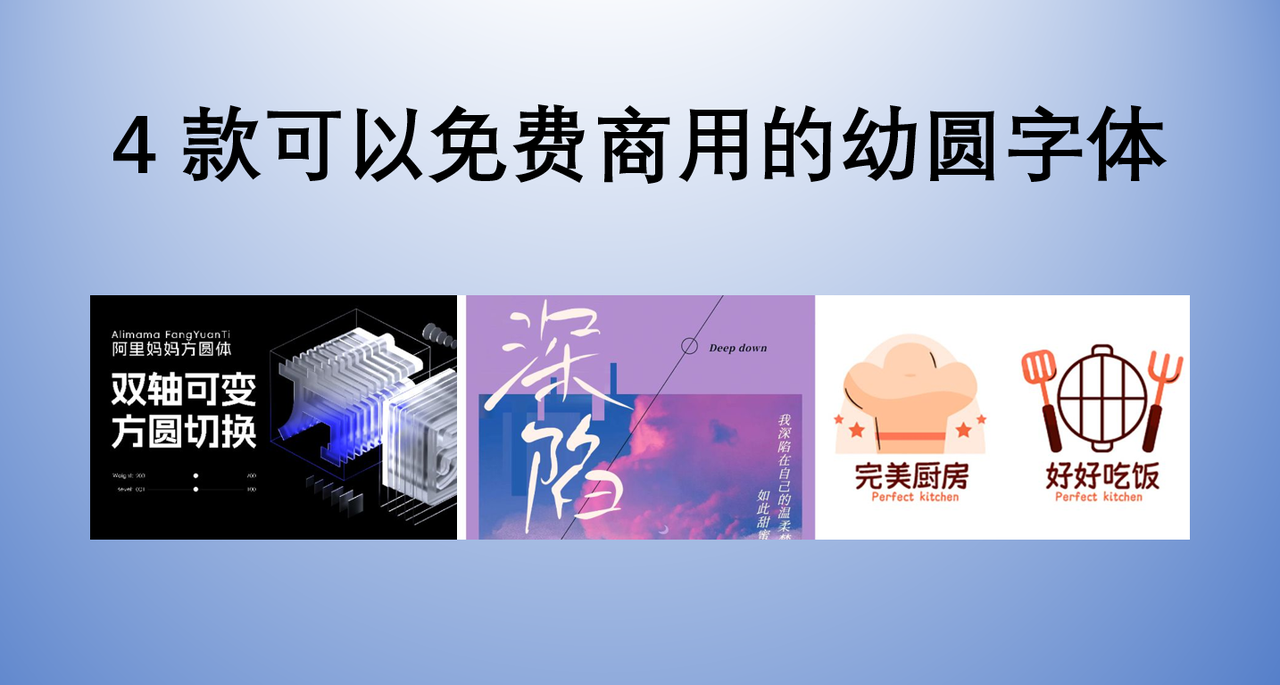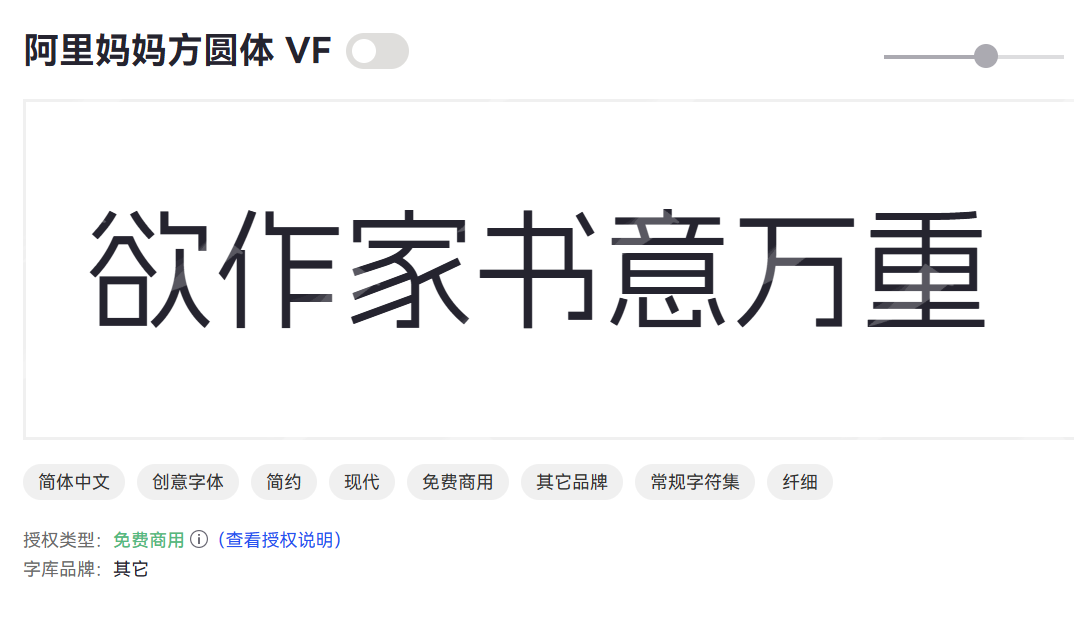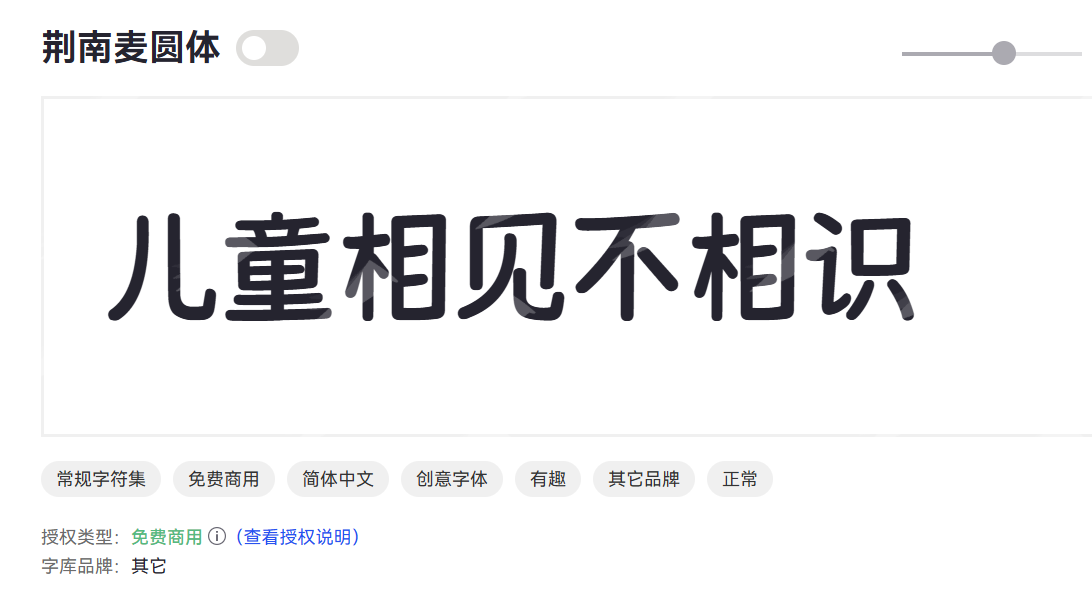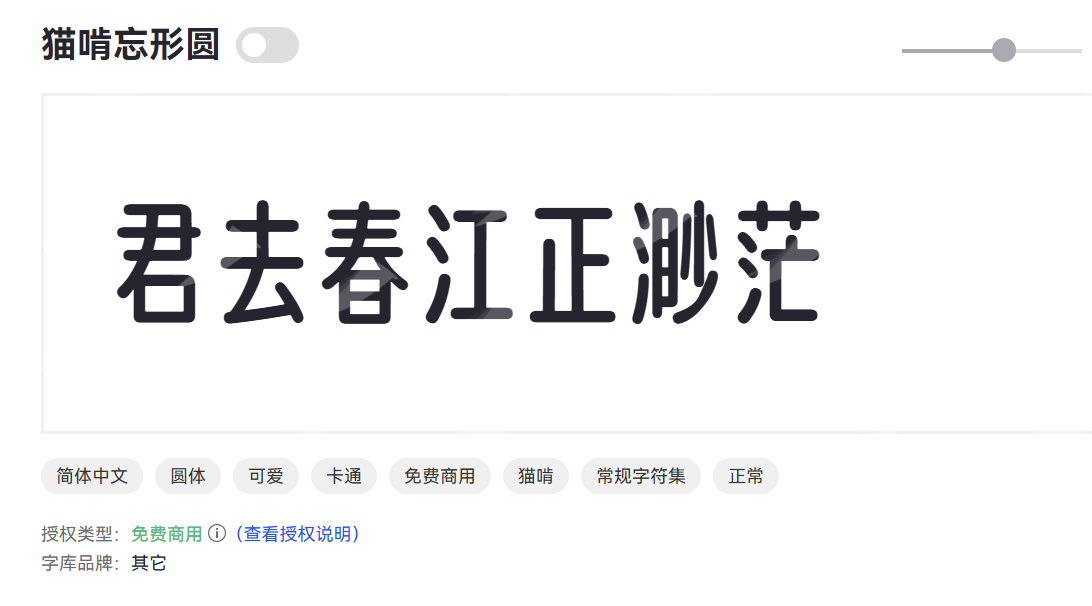
幼圆字体是否可以商用?4 款可以免费商用的幼圆字体
提起幼圆字体,你的脑海中是不是立刻浮现出那种笔画圆润、看起来温和又可爱的字形呢?它确实有着一种独特的魅力,让人感到亲切。但是,关于幼圆字体,尤其是它在商业使用上的问题,让不少设计师和商家吃过亏。别担心,今天我就来为大家介绍一下幼圆字体,并且给大家分享 4 款可以免费商用的幼圆字体。
1. 幼圆字体是什么字体?
从字体分类来看,幼圆字体可以归类为圆体字的一种,也可以看作是黑体字的一种变体。它在黑体的基础上,将笔画的直角和锐角都变成了圆角,使得整体风格更加柔和、轻松。它的字形结构清晰,笔画粗细适中,因此在保证可读性的同时,也大大提升了视觉上的舒适度。
从字面意思上理解,“幼”字可能让人联想到儿童、稚嫩,“圆”字则点明了它的核心特征。它是一种笔画圆润、结构饱满、字形端正的字体。它的笔画末端和转角处都经过了柔和的圆化处理,不像宋体那样有锋利的衬线,也不像黑体那样棱角分明。
1. 4 款可以免费商用的幼圆字体
阿里妈妈方圆体
我已经多次分享这款字体了,阿里妈妈方圆体是一款由阿里巴巴和方正字库联合推出的免费商用字体。它以现代感和实用性为设计核心提供一种既清晰易读又富有亲和力的视觉体验,尤其适合电商平台和数字媒体使用。
阿里妈妈方圆体字形端正,重心平稳,整体感觉沉稳大气。适合商品标题、详情页、促销海报、店铺招牌等电商场景,以及各类数字产品的用户界面和体验设计。
鸿雷拙书简体
鸿雷拙书简体是一款充满人文气息和艺术风格的字体。它以一种“拙朴”的书写姿态呈现,笔画看似不经意,实则蕴含着独特的韵律感和力量感。
线条不拘一格,带有手写墨迹的自然感和粗犷感。兼具传统韵味与现代审美,辨识度极高。非常适合一些文创厂家,比如艺术展览、纪念品等等。
荆南麦圆体
荆南麦圆体是一款充满温暖、柔和与自然气息的幼圆字体。它将麦穗的饱满、丰收的喜悦融入字形设计,笔画圆润而富有弹性,整体风格清新可爱。
荆南麦圆体线条柔和饱满,转角圆滑,富有亲和力,传递轻松、愉悦、充满童趣的情感。所以它非常适合一些儿童、家居相关的场景,比如童装、玩具、居家产品等等。
猫啃忘形圆
猫啃忘形圆是一款充满童趣和自由精神的幼圆字体。它的设计灵感来源于孩童涂鸦般的随性与无拘无束,笔画圆润可爱,字形略带不规则,仿佛忘记了传统字体的“规矩”。
猫啃忘形圆同样适合一些儿童、轻松的使用场景,比如绘本、儿童读物、动画片字幕、少儿教育App界面,或是游戏UI、表情包、漫画对白、休闲App宣传。
1. 幼圆字体的使用场景
1. 亲和力与童趣:
儿童读物、教育教材、玩具包装、少儿节目字幕、幼儿园招牌、母婴用品广告、儿童食品包装等。
1. 轻松与休闲:
零食饮料包装、休闲餐饮店招牌、时尚杂志的轻松小标题、个人博客/Vlog字幕、漫画对话框、社交媒体内容配图等。
1. 温馨与甜蜜:
烘焙店Logo、咖啡馆菜单、情人节/生日贺卡、婚礼请柬(作为辅助字体)、家居饰品广告等。